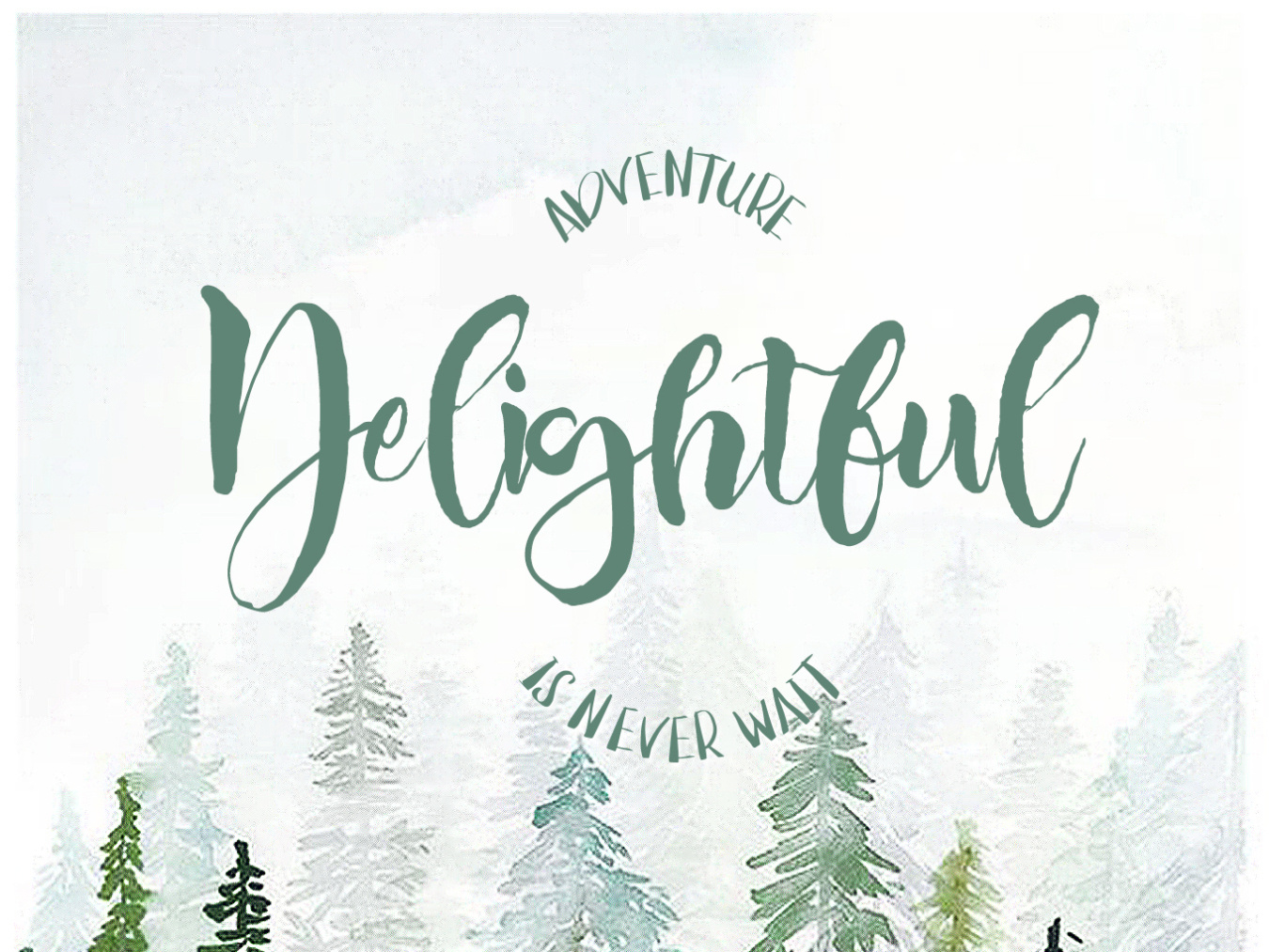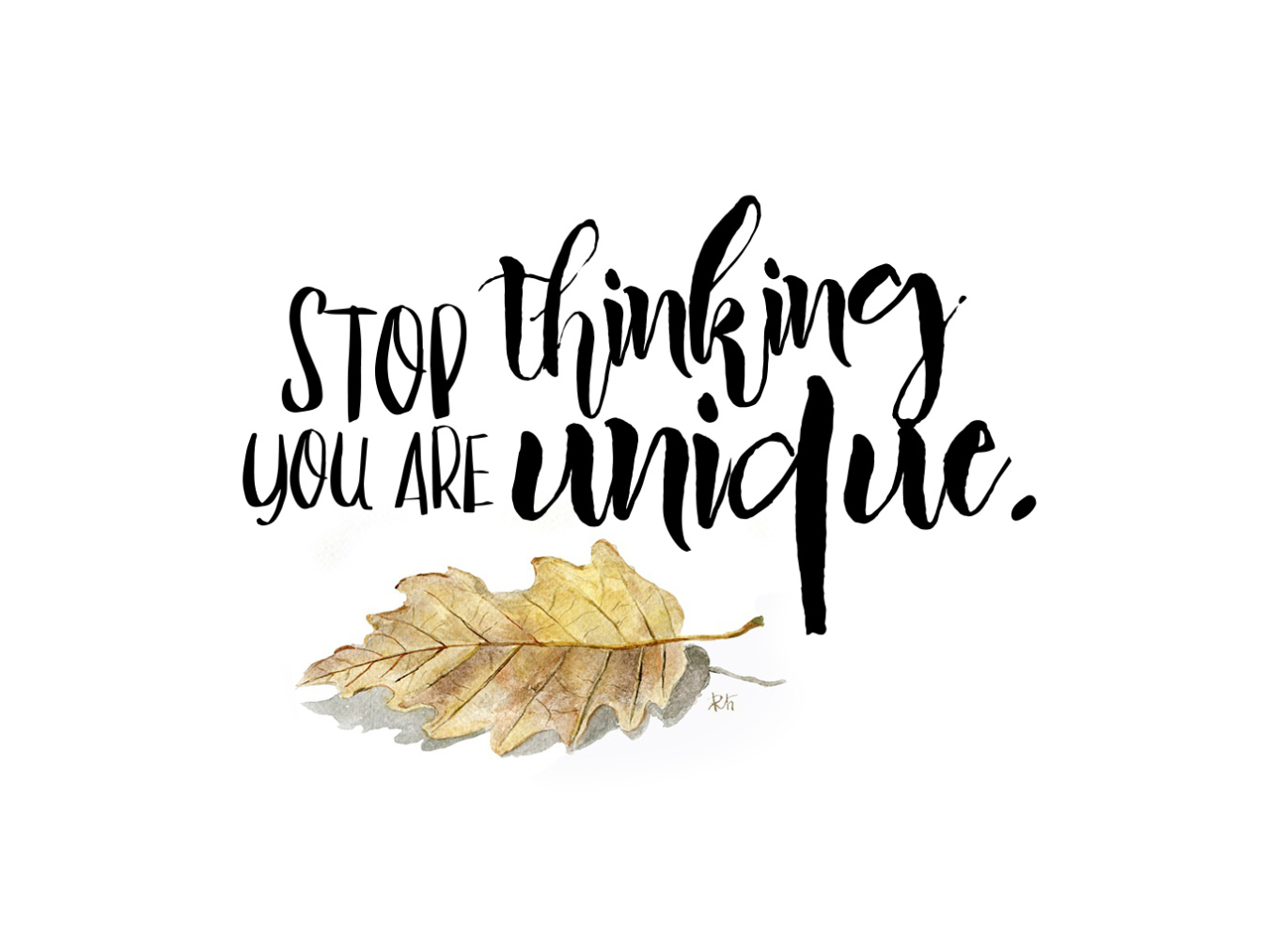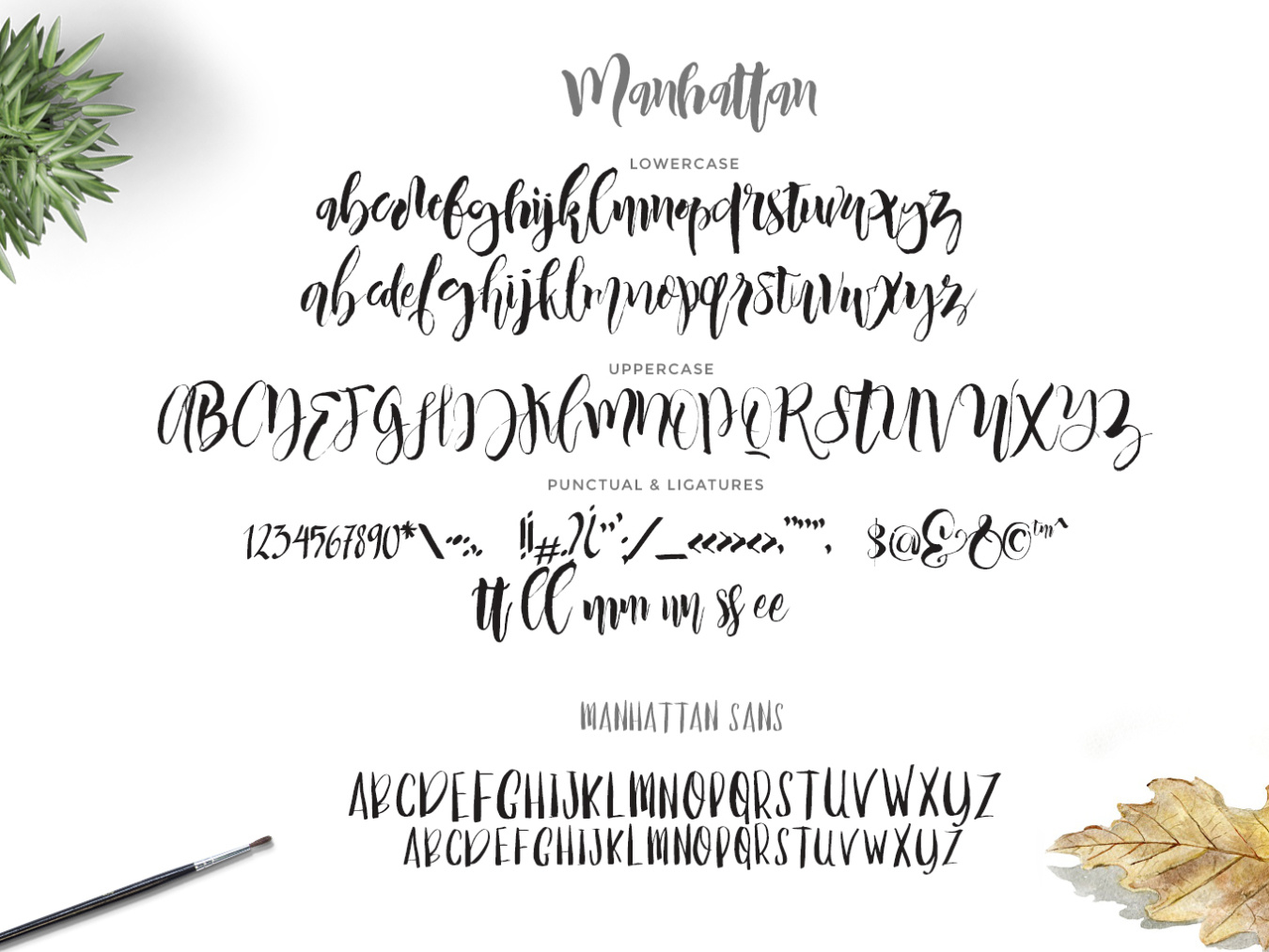
曼哈顿刷字体二重奏,曼哈顿刷字体二重奏
Manhattan Brush Font Duo, Manhattan Brush Font Duo
介绍曼哈顿脚本字体,这是一个手工制作的手写脚本,带有正宗的干刷瑕疵。曼哈顿的主要文件包含2种字体样式:曼哈顿脚本•包含大写和小写字符,数字和标点符号的手绘脚本字体,结合备用大写字符,因此您可以与自定义类型结合使用。曼哈顿sans•简单类型的大写字符可以成为一个伟大的非正式角色。 Ligature•自由选择的连字也可以在opentype软件中打开,因此自动将标准字母切换为提供的连字,指示字形显示以查看可用的连字字形。